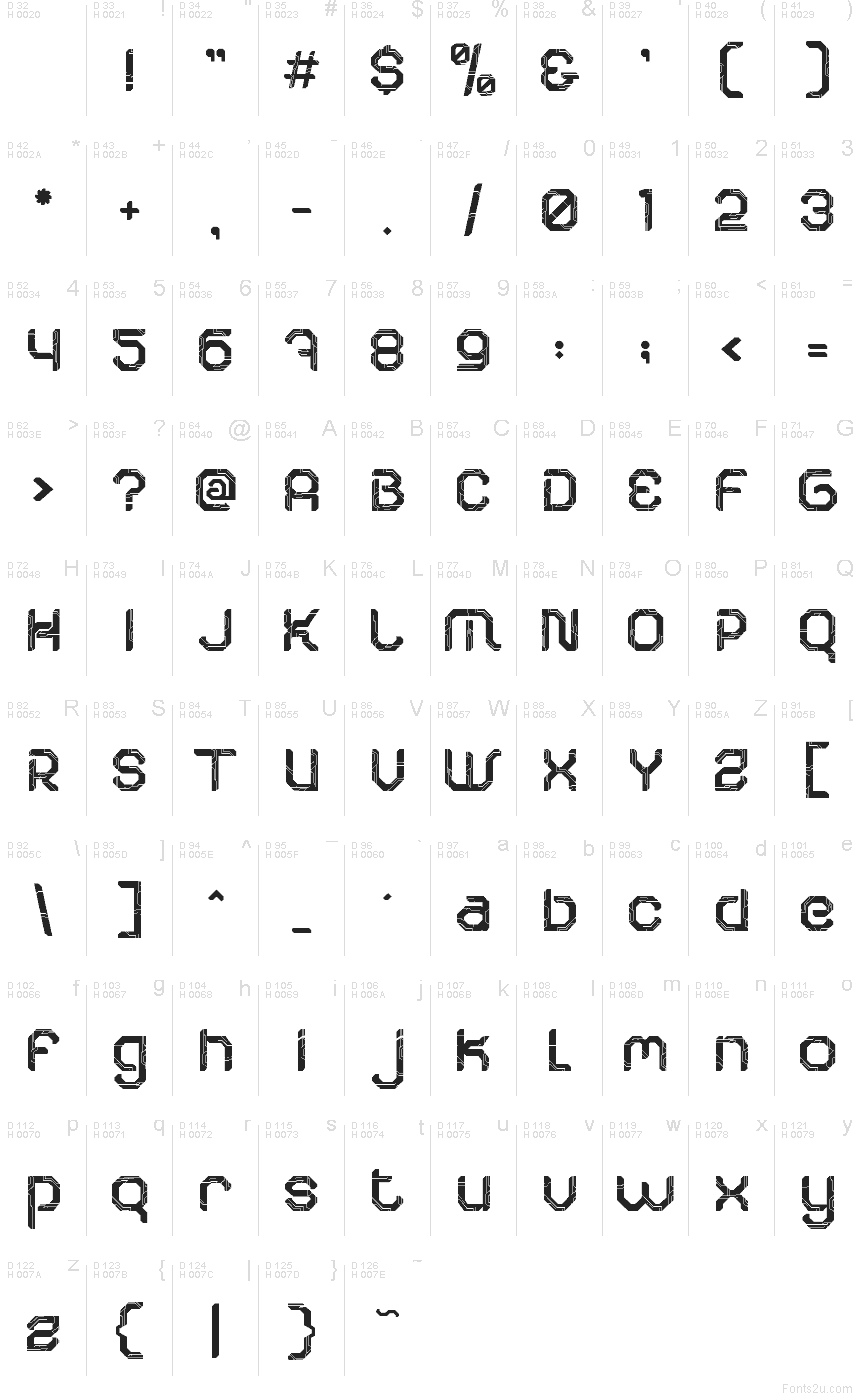
Snapshock One
Snapshock One od Putracetol Studio je futuristické bezplatné písmo typu display, pre ktoré je typický motív plošných spojov prechádzajúci cez každé písmeno. Hranaté vonkajšie tvary a úzke vnútorné línie dodávajú písmenám vzhľad zapojených hardvérových panelov. Dizajn tak nepôsobí ako bežné techno písmo, ale skôr ako cesty vygravírované priamo v hardvéri.
Vďaka tomuto prístupu je ideálnou voľbou pre herné tituly, sci-fi plagáty, streamovacie prekrytia, grafiku pre technologické podujatia a vizuály elektronickej hudby. Vykreslené linky dodávajú krátkym nadpisom energiu aj pred pridaním farieb či efektov a takisto dokážu zvýrazniť logá alebo UI branding, ktoré si vyžadujú digitálny systémový vzhľad.